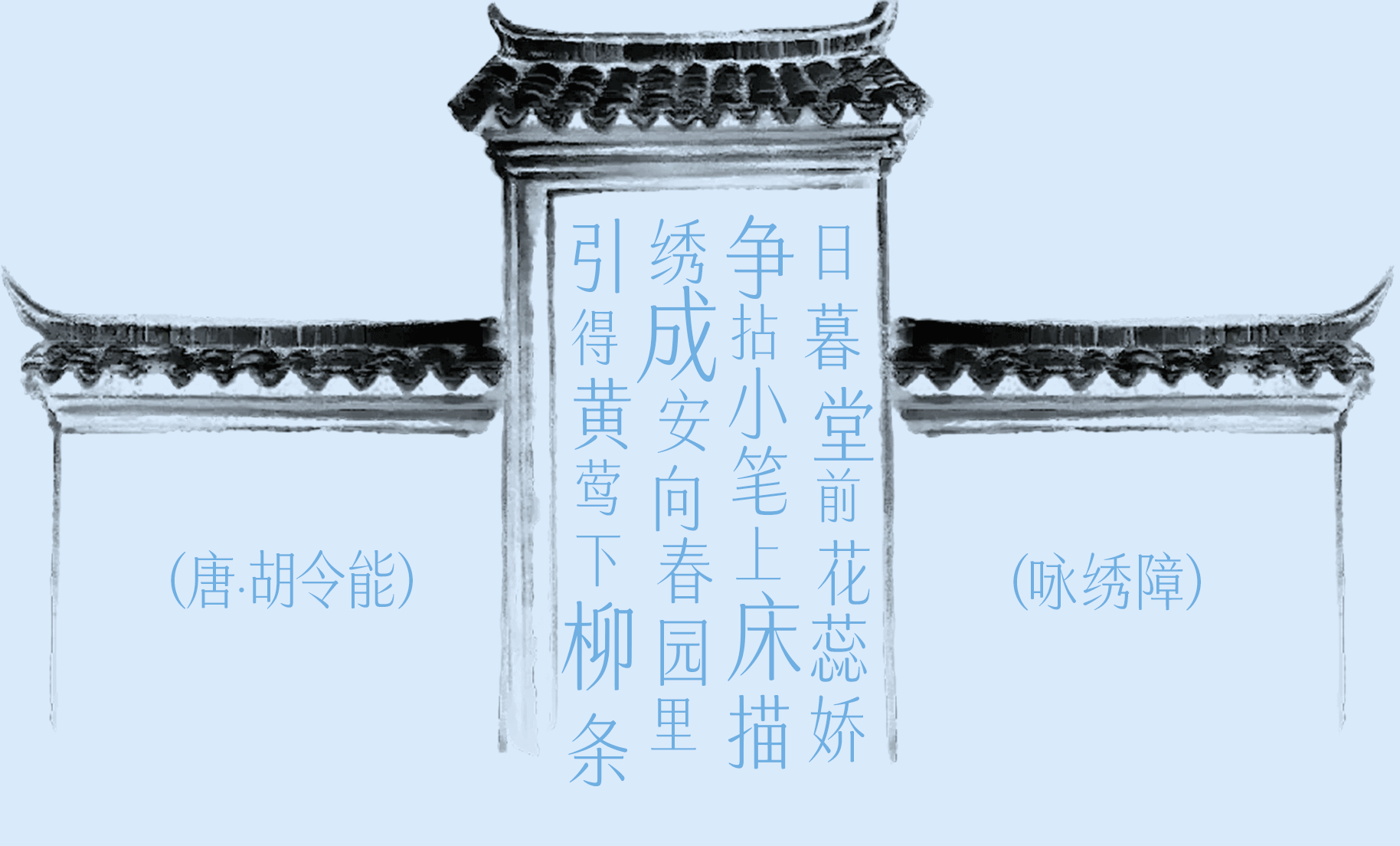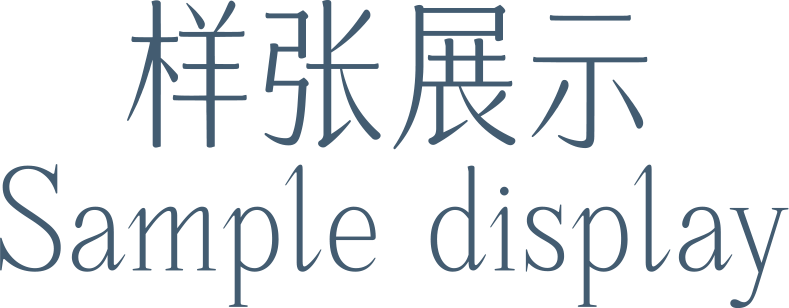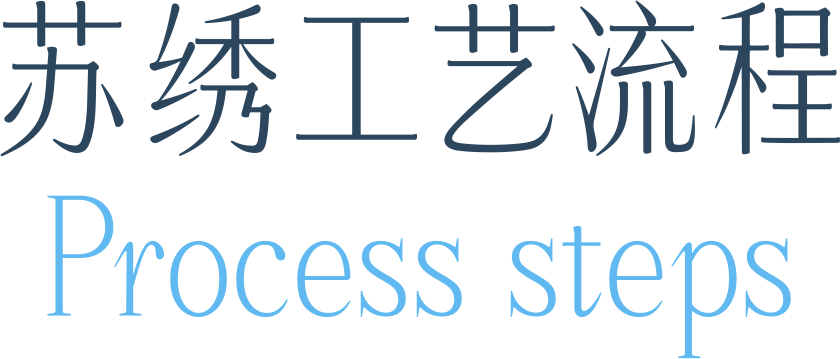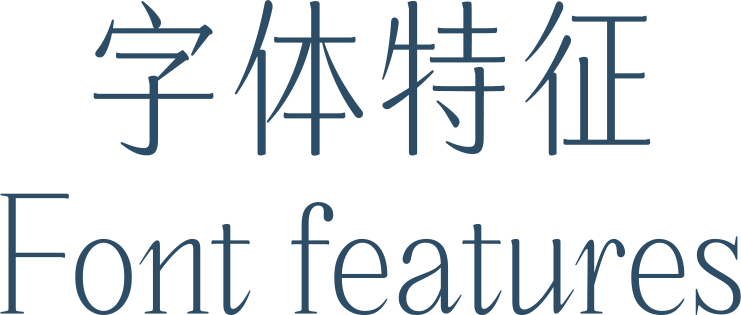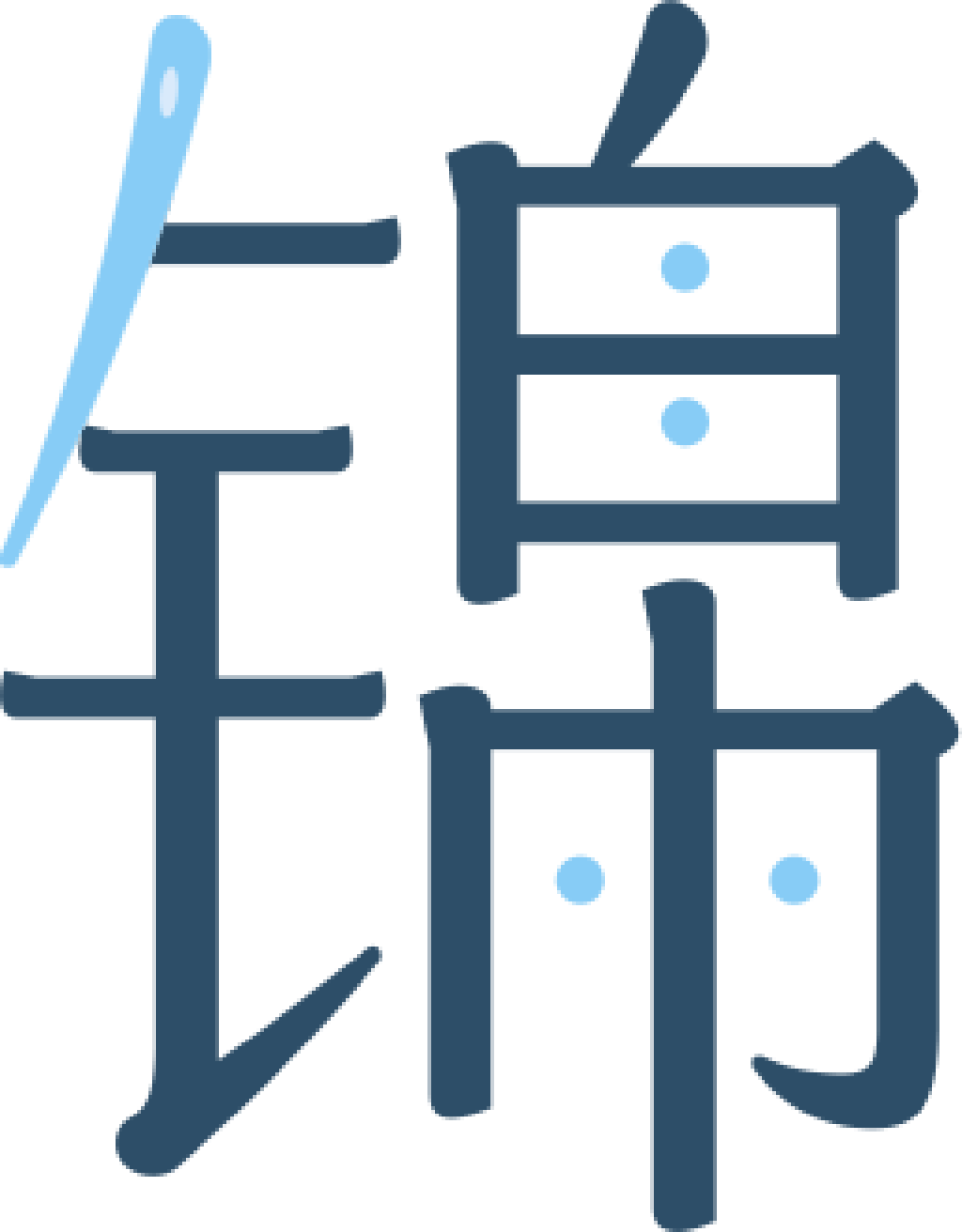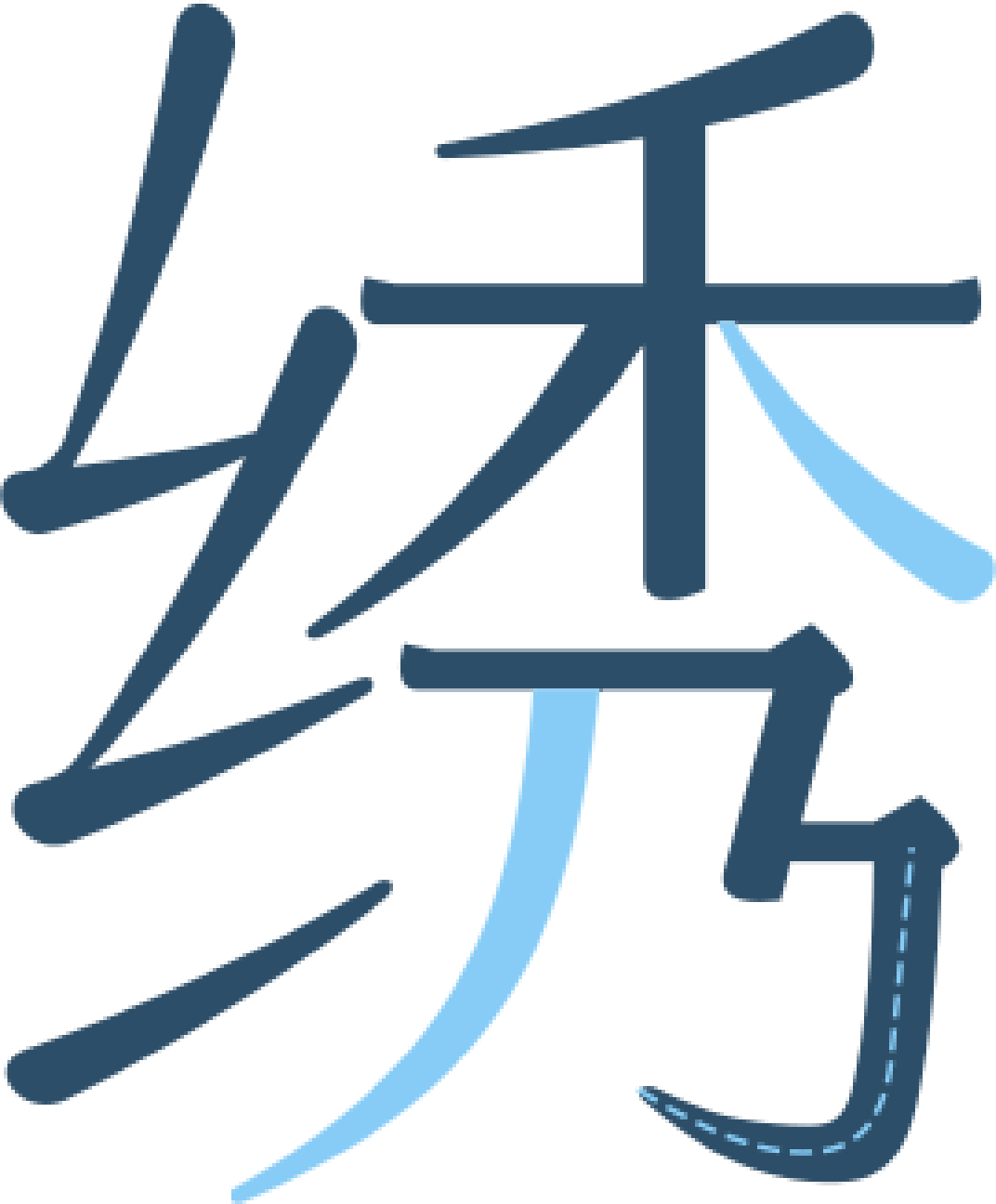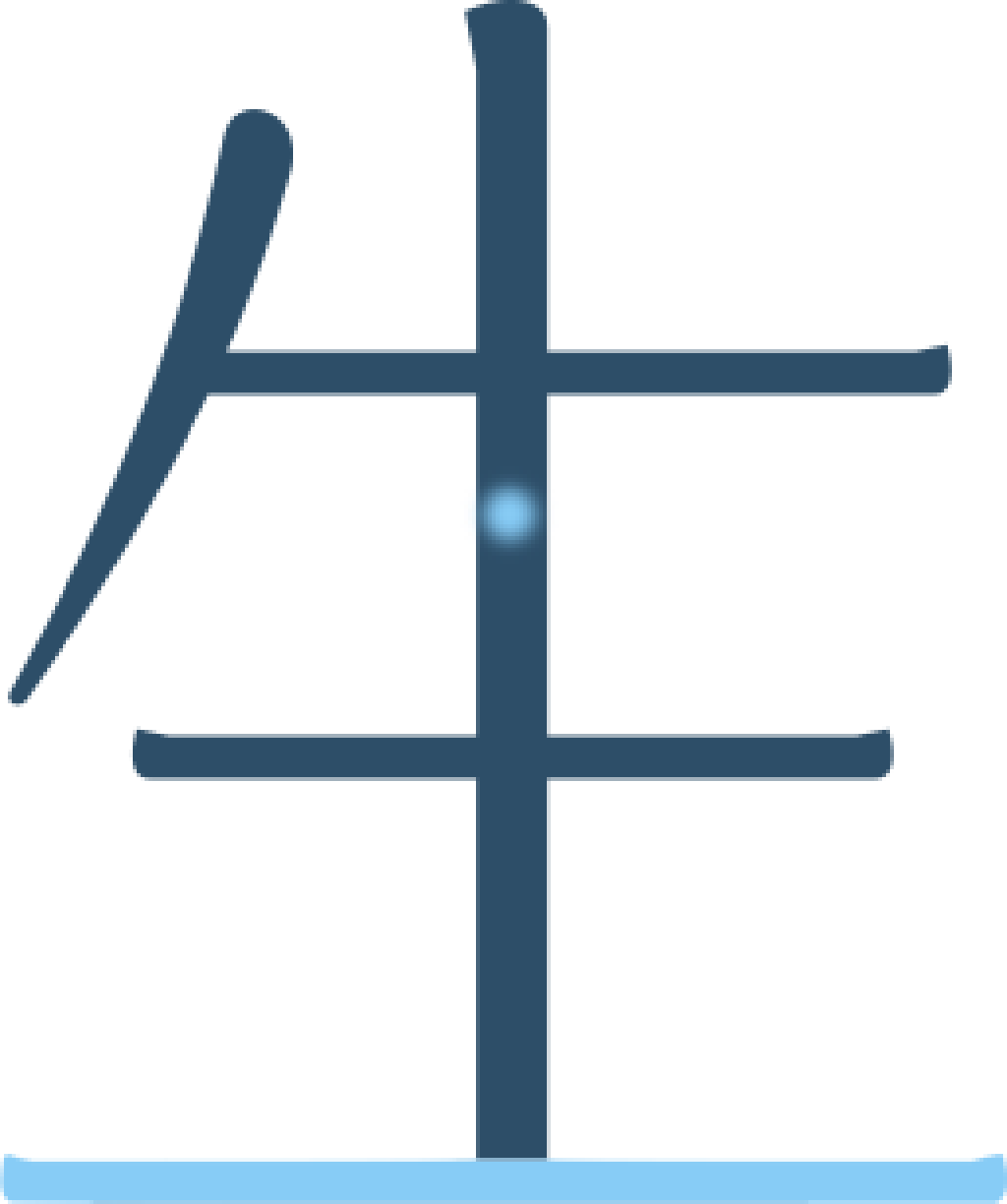
苏绣,传承两千余年,冠绝中国四大名绣。
一根丝线能劈至一百二十八分之一细,一件精品苏绣需近百万针绣制。绣娘凝神屏意,日复一日,方得佳作天成。
细密针脚,含蕴着江南的温婉灵秀;流转丝线,珍藏有非遗的坚守传承。
字魂创意字库与吴文化博物馆携手,从苏绣技艺中汲取灵感,
将针尖上的匠心融入笔墨之间,为其定制设计「字魂吴文化博物馆苏绣体」。
于笔画流转处,邂逅苏绣的千年风华。
字魂吴文化博物馆苏绣体,从苏绣非遗技艺中汲取灵感
将代表性的绣针造型融入笔画,让东方之美焕发于字里行间
字形刚柔并济,灵动秀雅
既似苏绣精品,温婉考究;又如江南女子,亭亭玉立
点画
针尖入画,灵动优美
竖画
绣针挺立,笔直轻巧
撇捺
丝线轻摆,流畅活泼
绣线舒展,柔丽飘逸
延续“绣花针”设计灵感,增加以手写痕迹,使西文字体更多一份温度与人文主义
使用狭窄字符间距排版时,西文尖角部分会产生特殊的粘连效果
使文案有如绣线织帛、春蚕吐丝,有着缠绵婉转的装饰性
居中的字符轴线,使造型中正稳定、简洁现代
有如苏绣丝线的灵巧韧性,整个笔型修长而纤细
生硬尖角化为圆润弧度,展现出温润雅致的东方气韵
当苏绣的丝线,在指尖缠绕出山水花鸟,那些针脚里藏着的
是前人对美的执着,也是时光也偷不走的细腻
苏绣的惊艳,绝不是 “非遗” 二字所能道尽
它是绣娘凝视纹样时的匠心,是丝线刺过布面时的轻响,是千年里从未褪色的生活美学
将苏绣的灵动绣进横撇竖捺,以新的载体与之共鸣
非遗之美就此融入了日常表达,拥有了生生不息的生命力
我们不想让这份瑰宝仅仅停留在被致敬的名单上
因为最好的传承,从来都是让美,永远在场